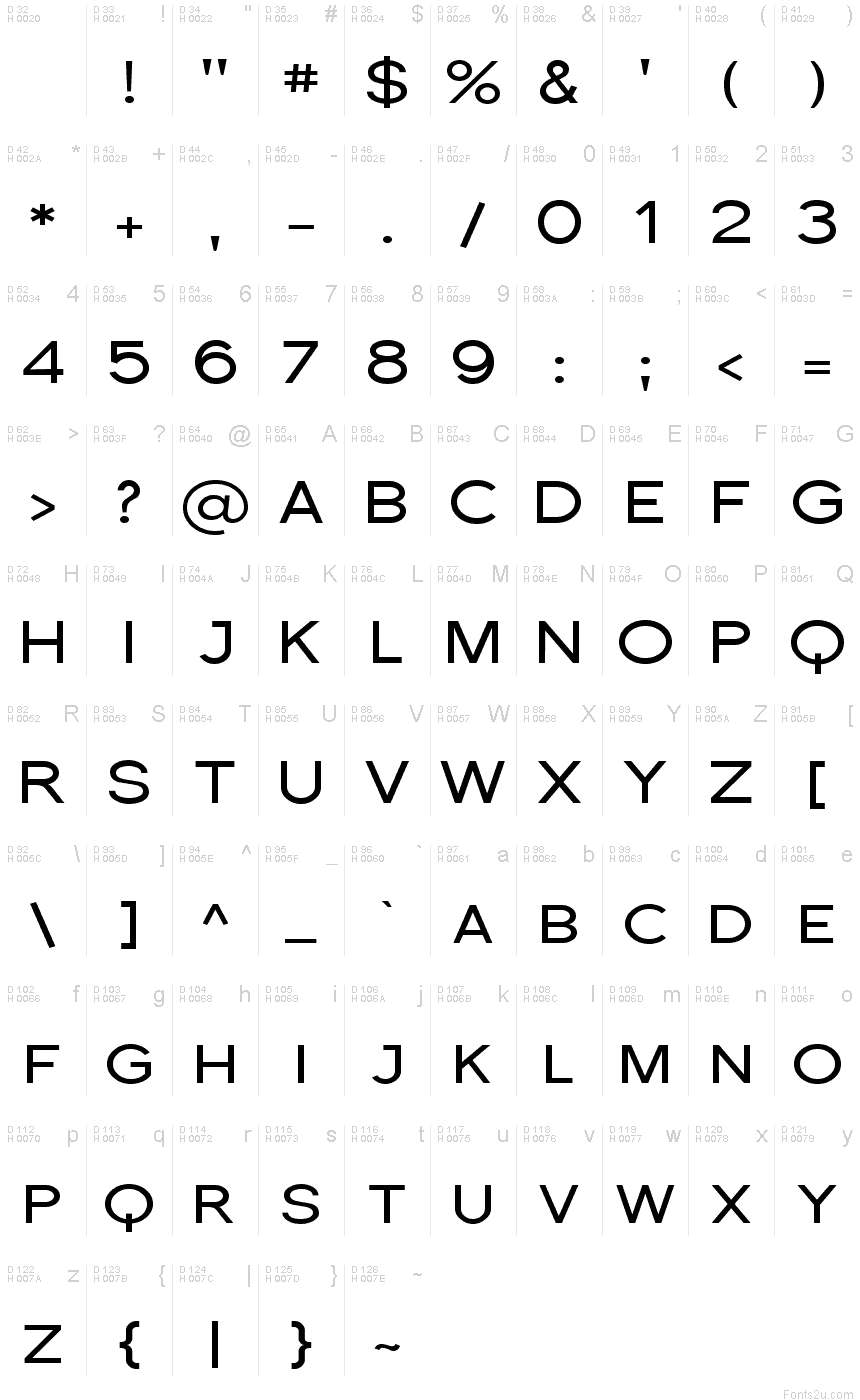
Florencesans SC Exp
Florencesans SC Exp autorstwa Dereka Vogelpohla to darmowy bezszeryfowy krój pisma o wyraźnie wydłużonej, architektonicznej formie. Litery są szerokie, mają równomierną grubość i ostre krawędzie, dzięki czemu każde słowo wygląda, jakby zostało starannie wyryte na eleganckiej metalowej tabliczce. Zaokrąglone łuki i otwarte światła wewnątrz znaków łagodzą geometrię, nadając całości chłodną, nowoczesną elegancję, nie sprawiając wrażenia czegoś zimnego czy mechanicznego.
Dzięki Florencesans SC Exp Twoje nagłówki układają się w czyste, poziome pasma, które są czytelne i wyrafinowane. Ten darmowy font świetnie sprawdza się w wyrazistych logotypach, brandingu marek modowych i lifestylowych, na plakatach, okładkach płyt, opakowaniach produktów oraz w grafice internetowej, gdzie zależy Ci na subtelnym dramatyzmie. Połącz szerokie wielkie litery z prostym, wąskim bezszeryfem w mniejszych rozmiarach, aby uzyskać mocny kontrast edytorski, który zachowuje równowagę i czytelność układu.